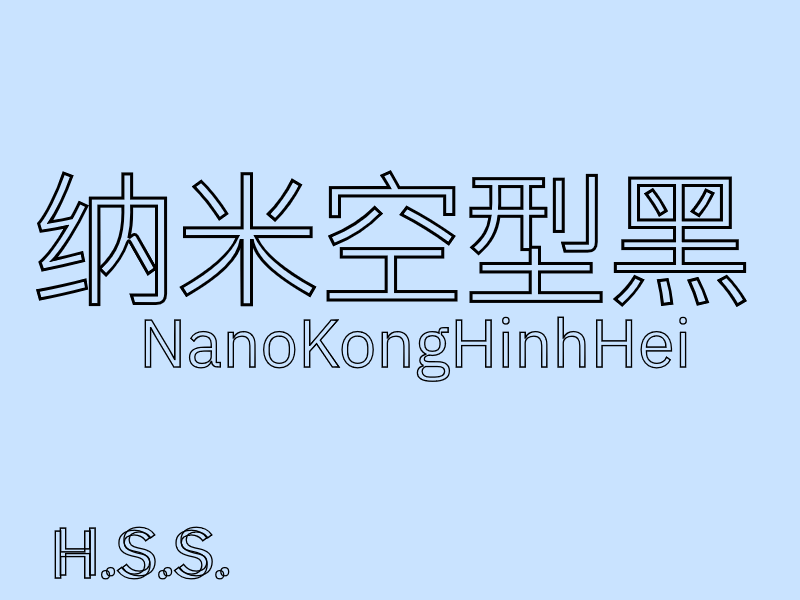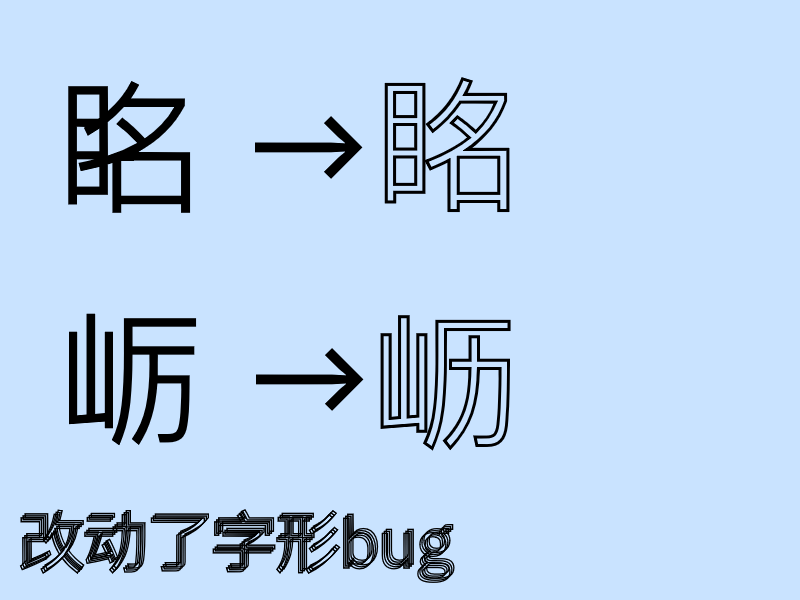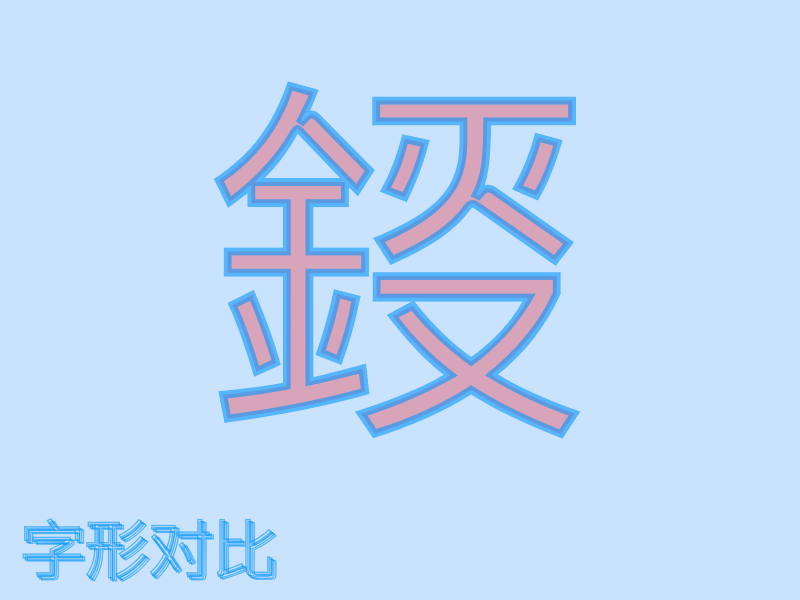
纳米空型黑走的是挖空路线,骨架底子直接选了IBM Plex SC做底座,随后顺着实际排版需求补了些细节。开发时顺手把原版里常有的字距偏移、局部比例失衡这些显示小毛病理顺,确保落到页面上结构能稳稳咬合。镂空处理没走捷径,直接延续NanoKwangHei的底稿逻辑,不靠硬切笔画,而是顺着原本的书写走向,一步步把内部实心区域向内抽离。外轮廓依然保持力度,但字面中央留下的自然空隙,让整段文字铺开后,视觉上多了一截透气的呼吸余地。